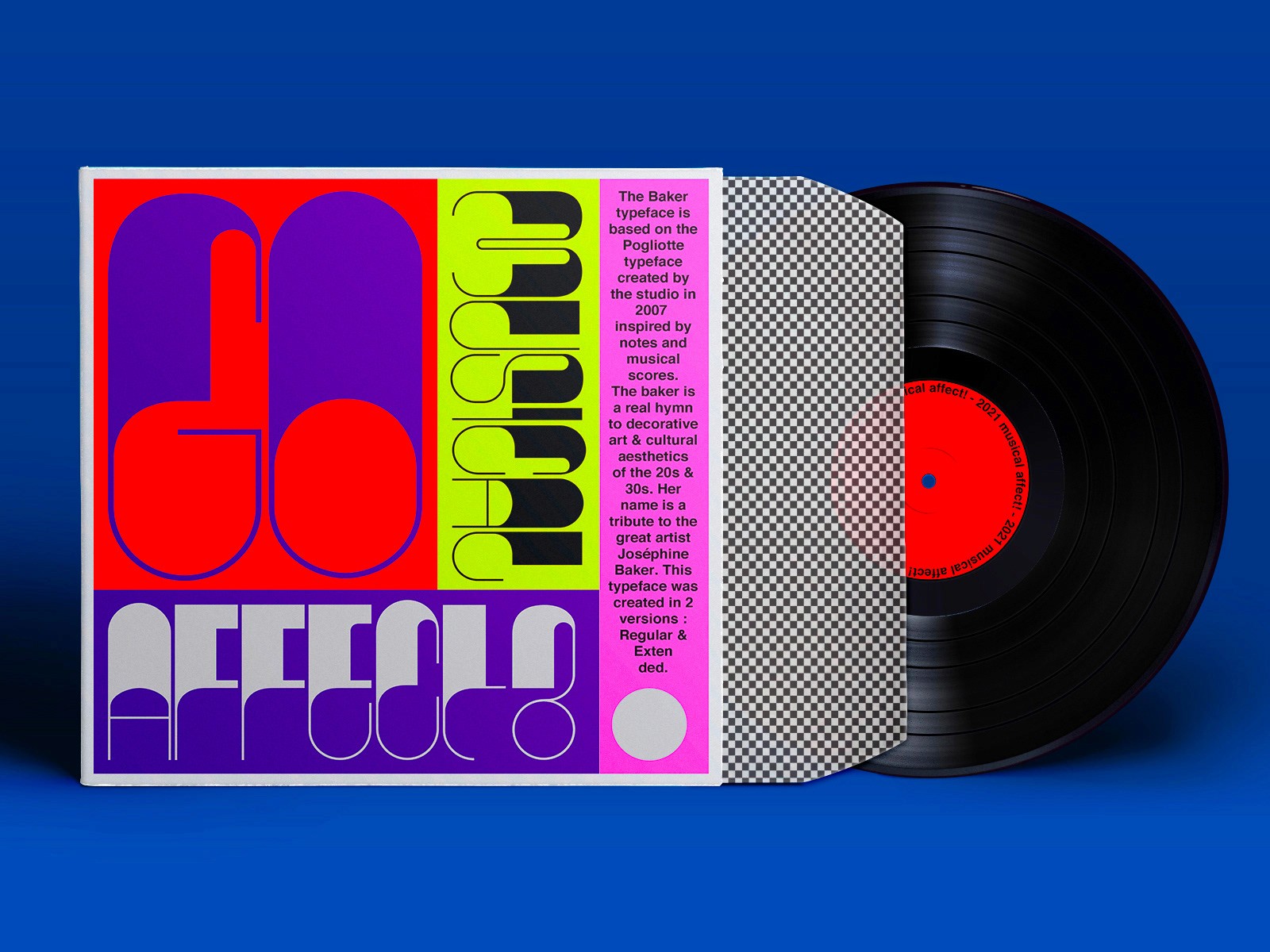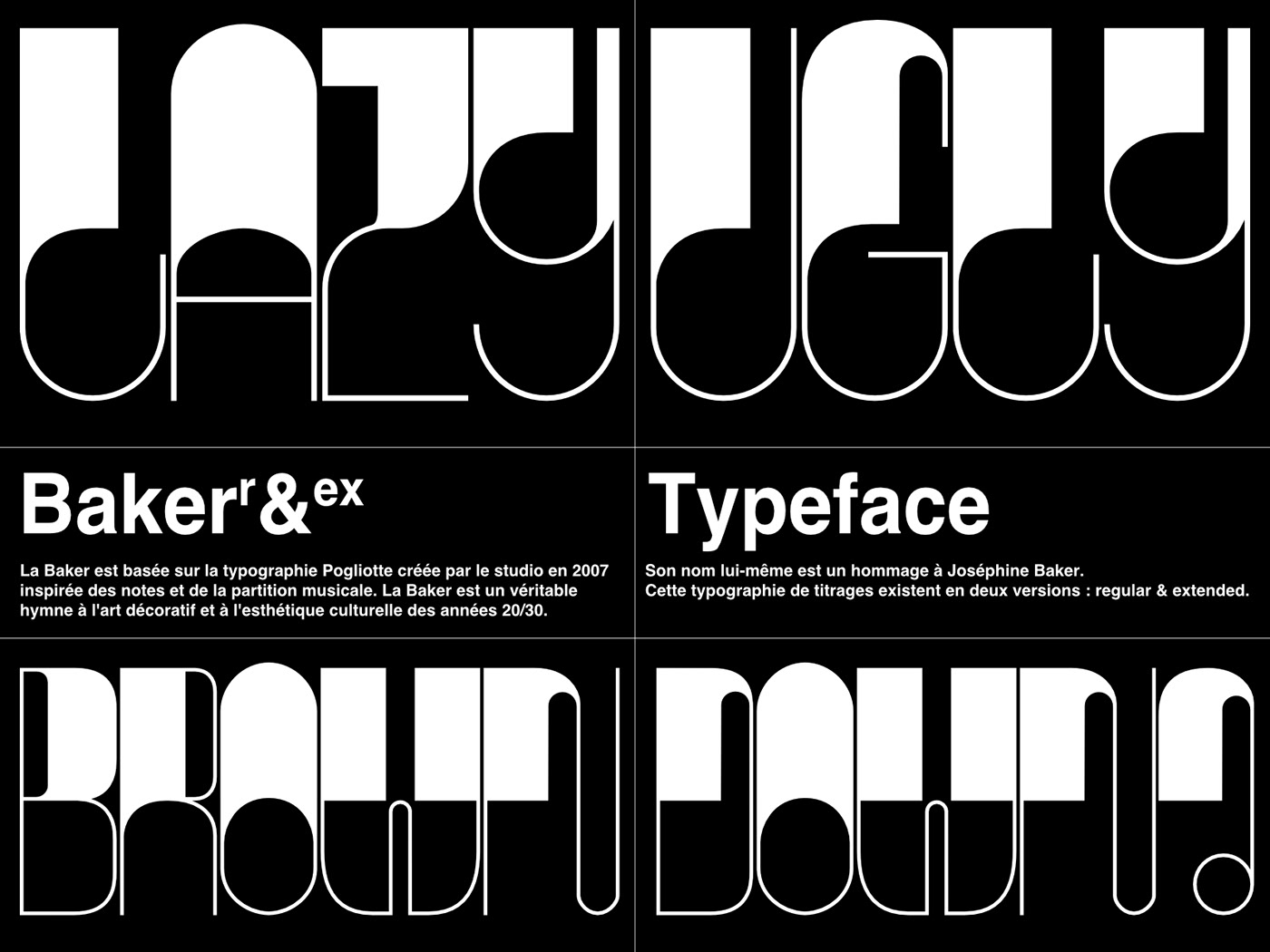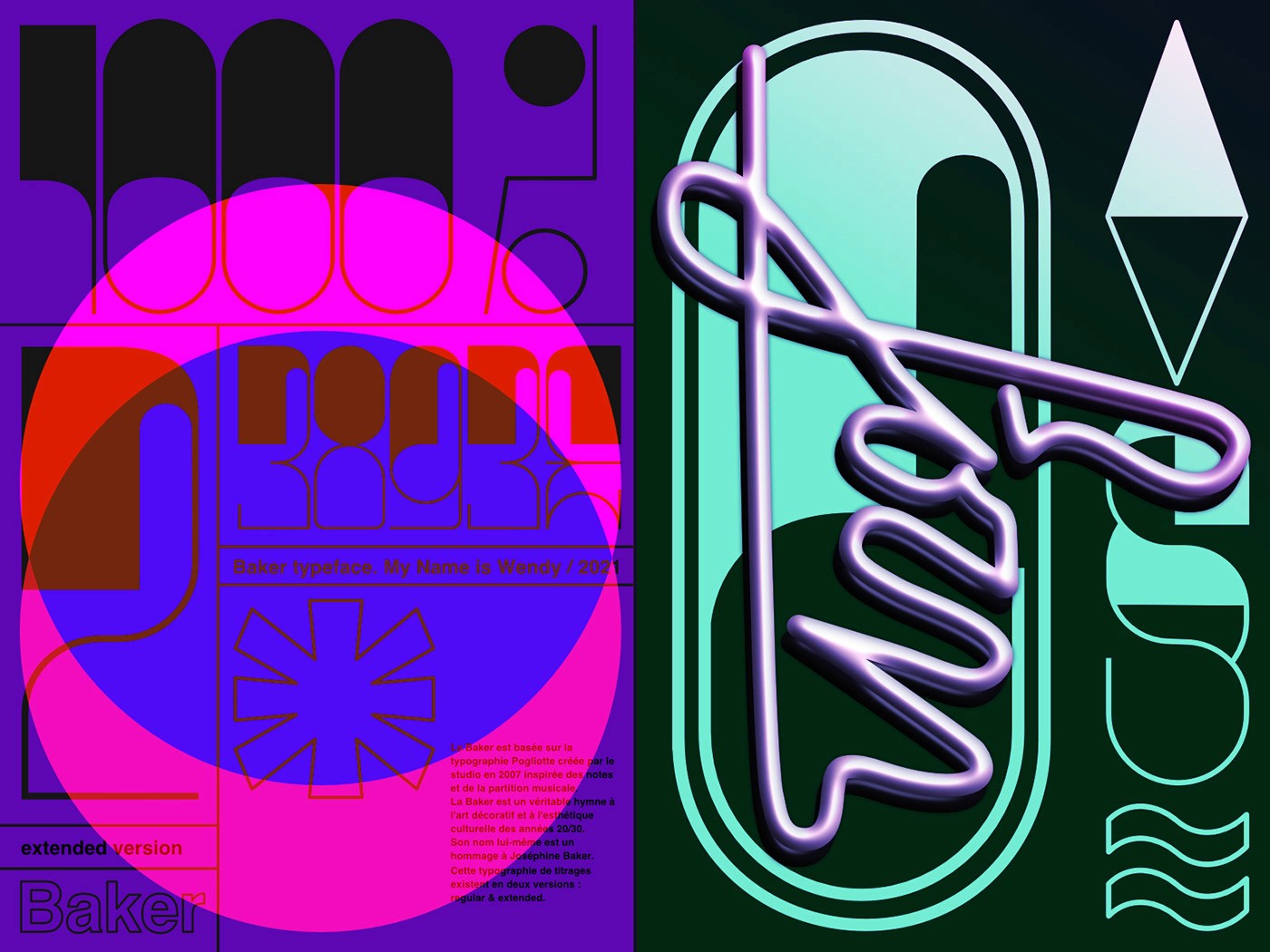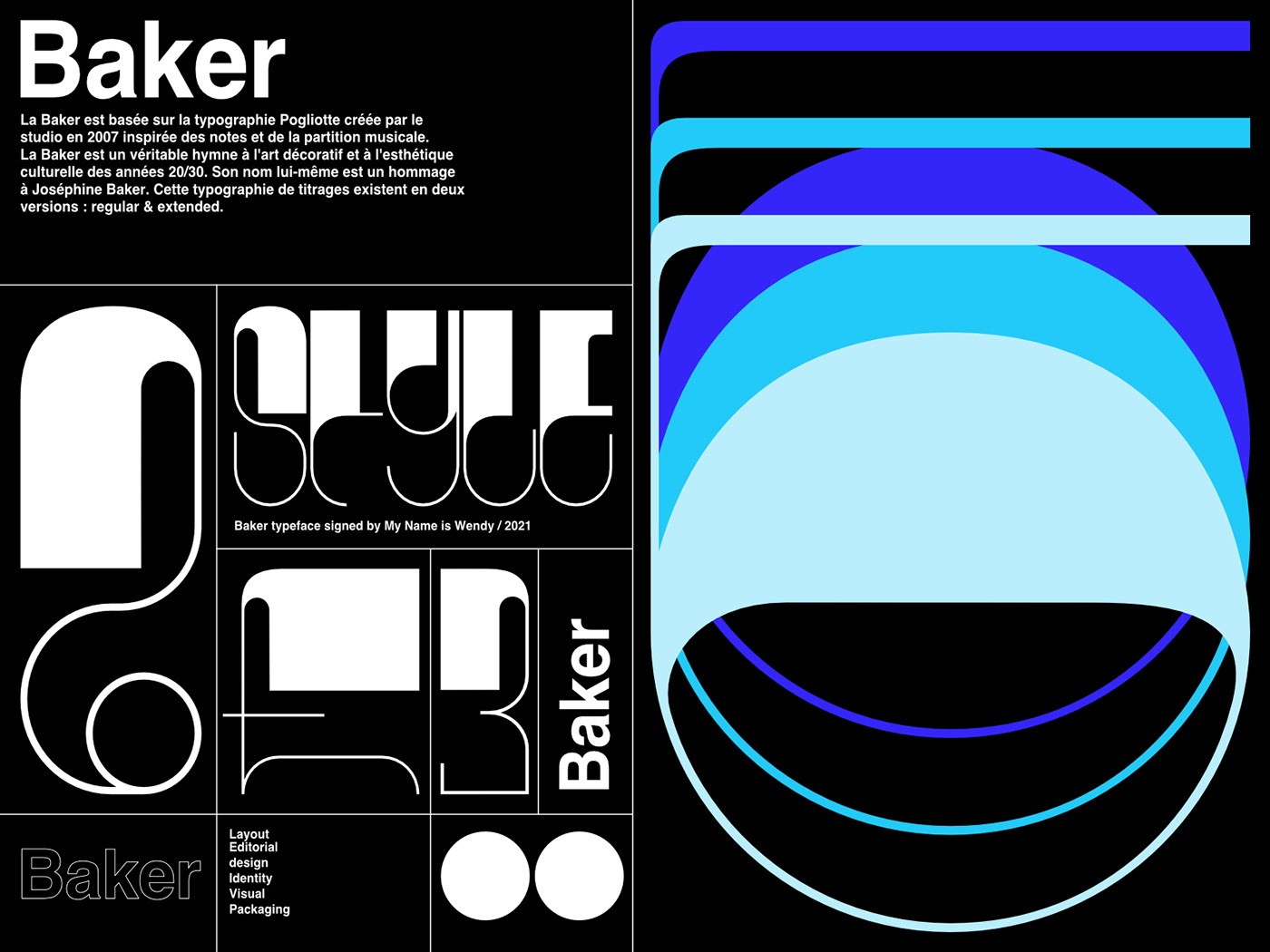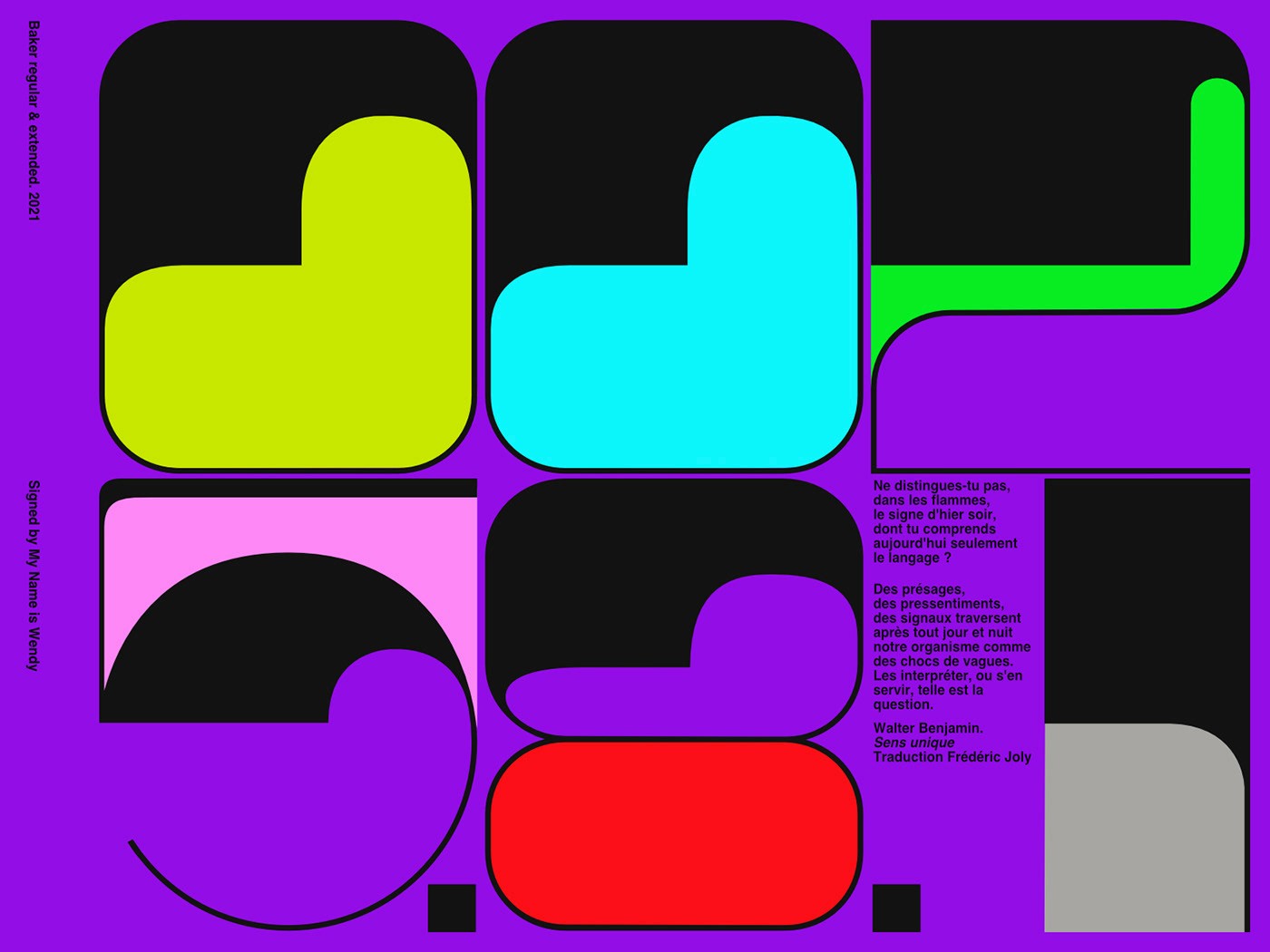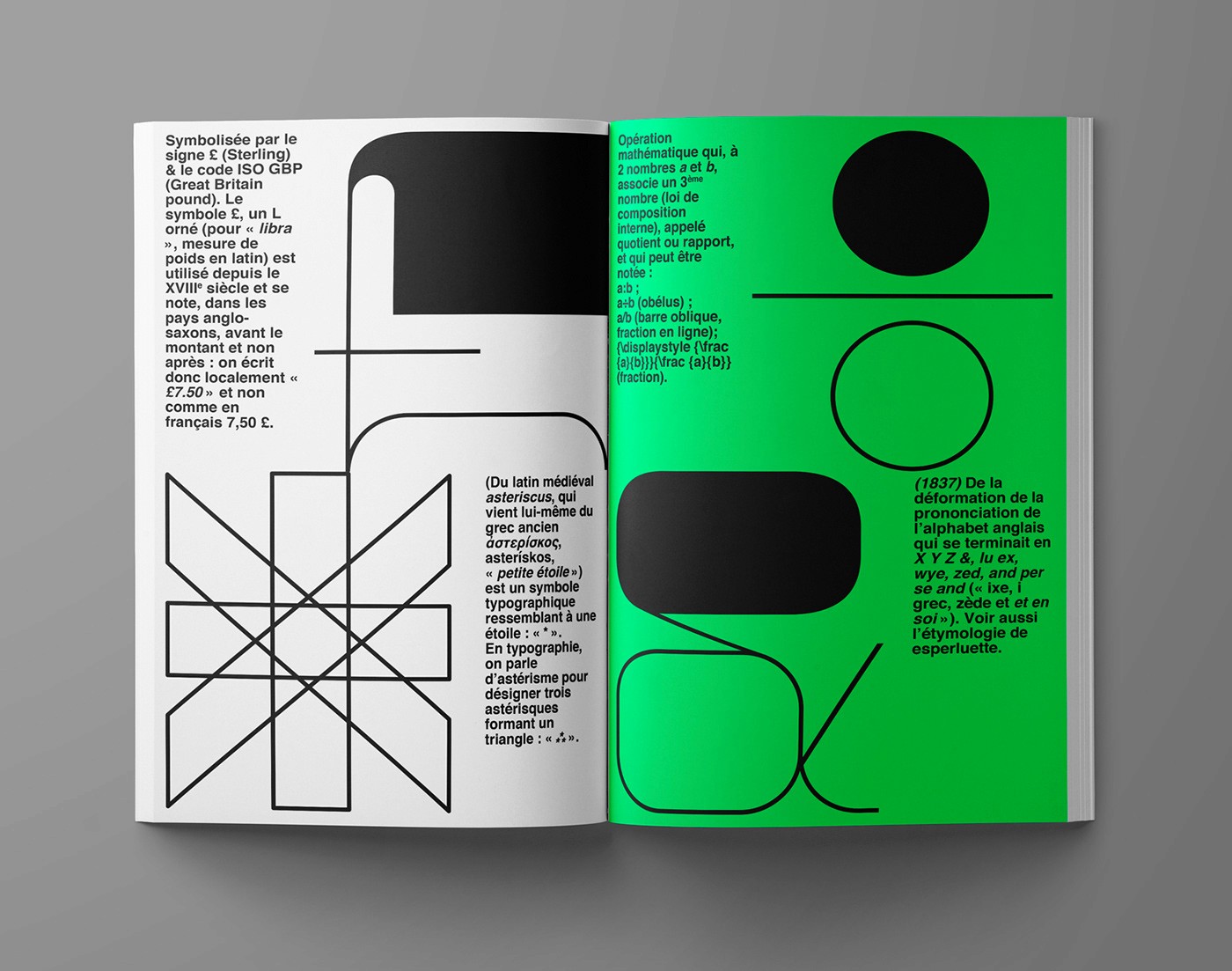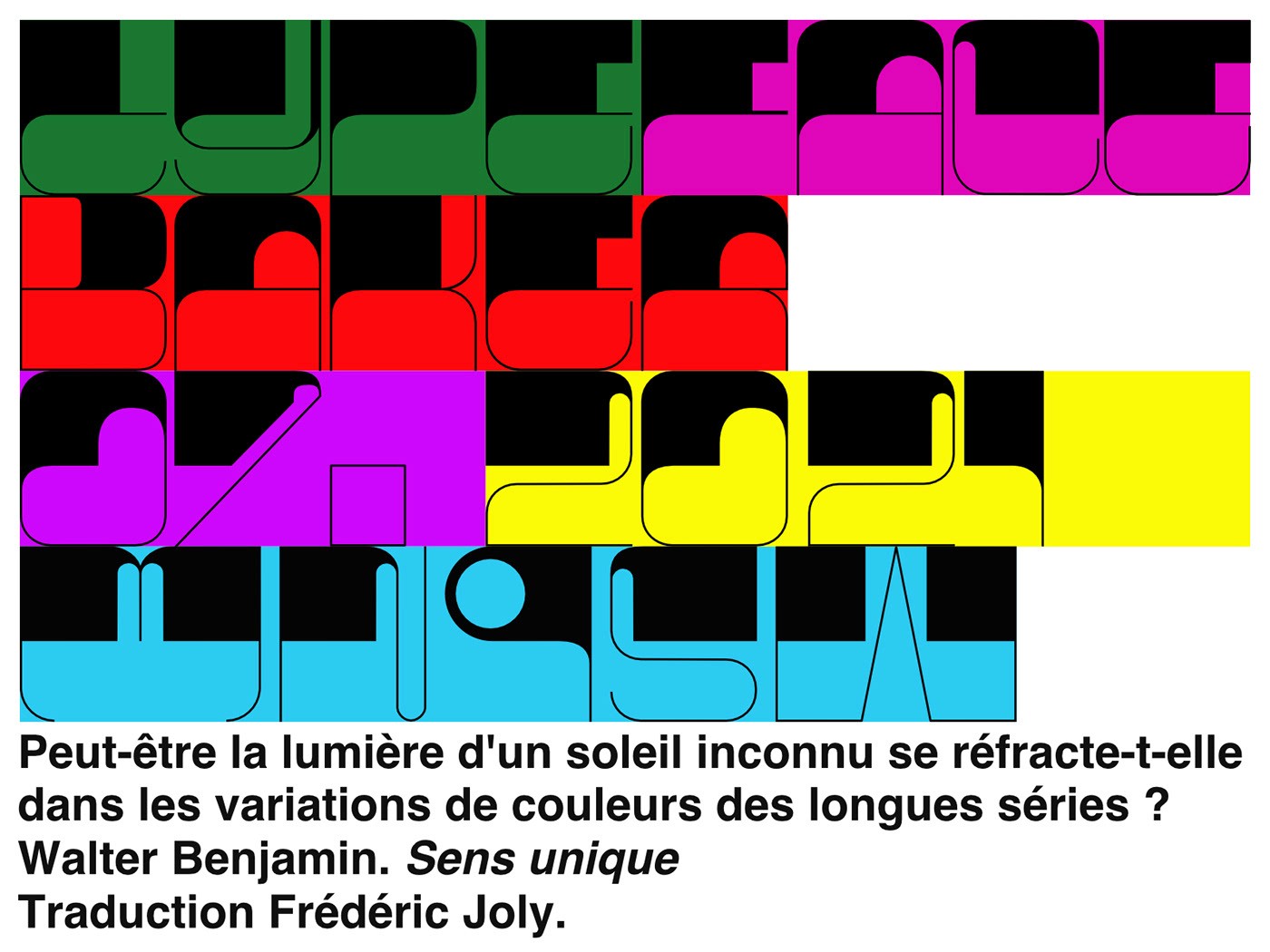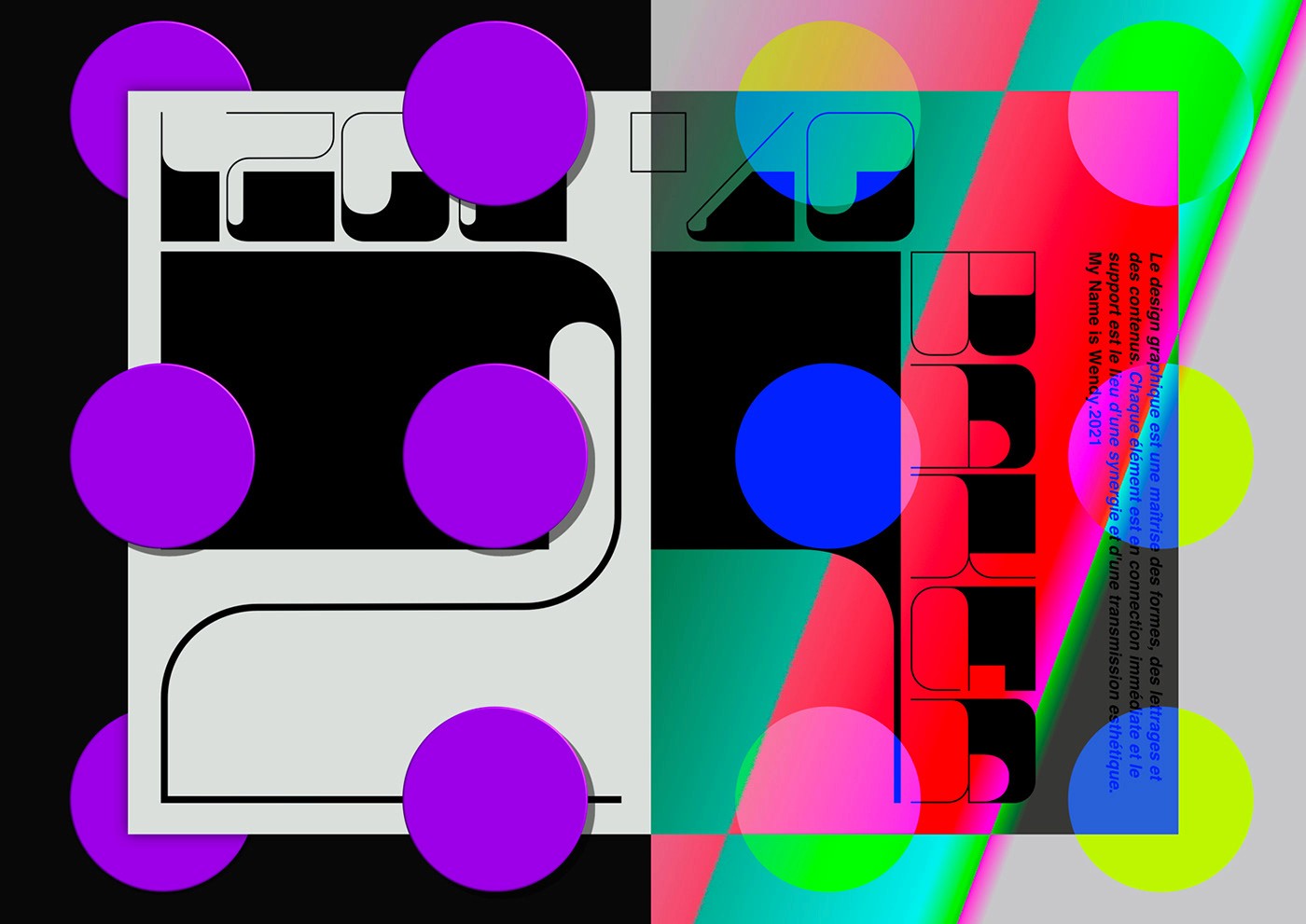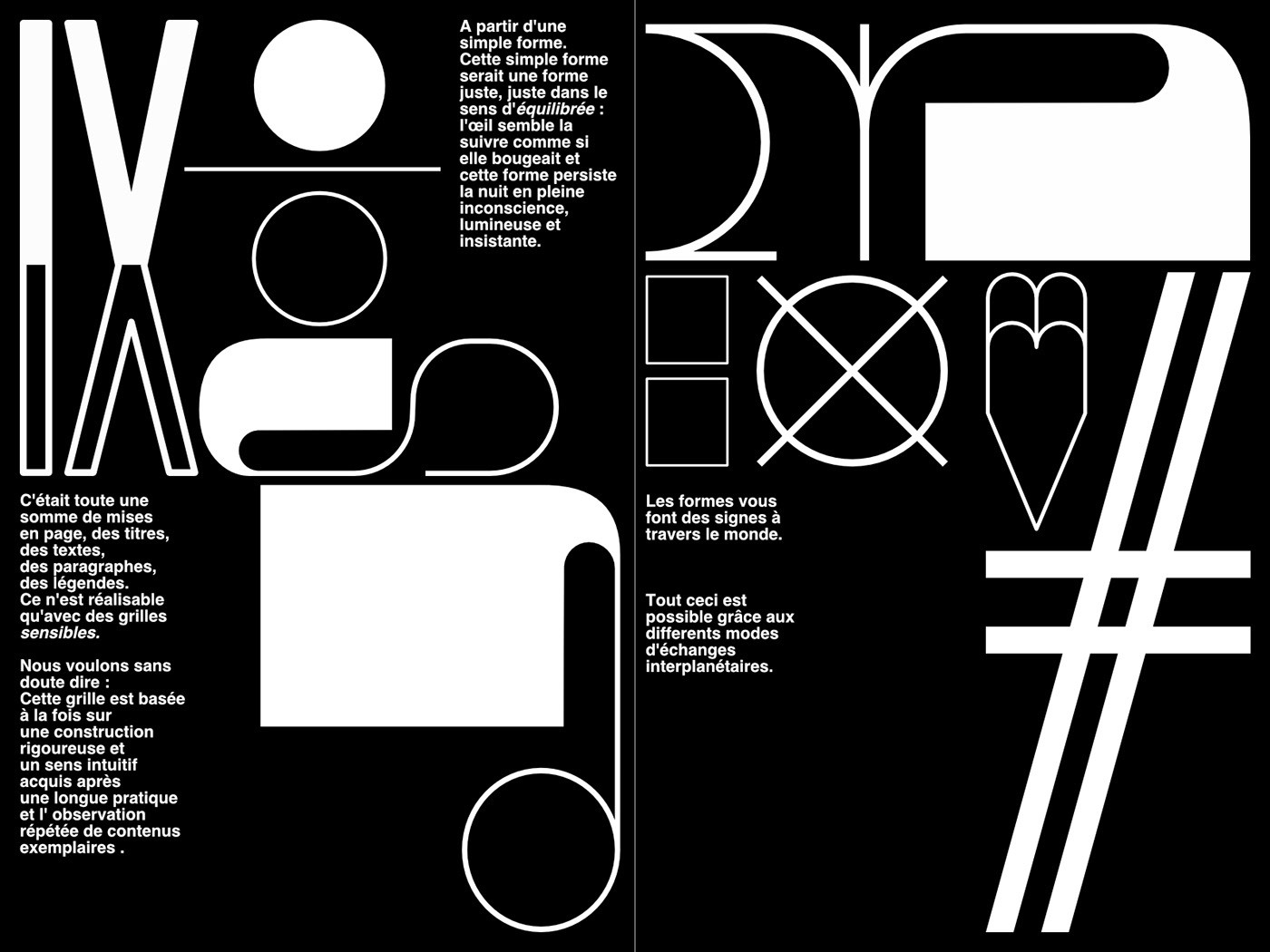
Baker Typeface - Bộ chữ độc đáo từ biểu tượng Josaphine bất hủ
Được truyền cảm hứng từ phong cách đặc trưng của nữ hoàng kịch nghệ tài năng âm nhạc người Pháp Josephine Baker, bộ font chữ Baker Typeface đã đem đến toàn vẹn tinh thần tươi mới và hơi thở phóng khoáng của một trong những biểu tượng có sức ảnh hưởng to lớn nhất trong văn hóa đại chúngMùa hè năm 1926 trong một buổi biểu diễn nhạc Jazz thường niên tại nhà hát nổi tiếng La Revue Nègre (Paris), một nữ nghệ sĩ da màu trong bộ váy độc nhất vô nhị được làm từ 16 quả chuối cao su cùng với những màn lắc hông điêu luyện của vũ điệu Dance Sauvage đầy khiêu gợi và đam mê đã khiến cả đám đông reo hò và gần như điên dại. Và từ đó Josephine Baker đã tạo một tiếng vang lớn và trở thành một hiện tượng văn hóa quyến rũ, xinh đẹp và tài năng.
‍Khi mới thoáng nhìn, ta có thể cảm nhận ngay nguồn năng lượng gần như là bùng nổ của nữ nghệ sĩ đình đám Josephine bởi sự tương phản cực mạnh giữa thân chữ rất dày và chân thì quá mảnh. Tuy nhiên không vì vậy mà trông chúng thô kệch hay nặng nề mà ngược lại đầy tính giai điệu và vô cùng duyên dáng bởi phần chân chữ được tạo hình với những nét cong mô phỏng các nốt nhạc. Và cũng không quá lời nếu ta liên tưởng đến những chuyển động tay chân nhuần nhuyễn điêu luyện của cô. Hơn thế nữa, phần dày nhất của bộ font chữ cũng rất tinh tế gợi đến hình ảnh nụ cười với hàm răng trắng sứ tỏa sáng đặc trưng đúng chất Josephine. Chính vì tính liên tưởng siêu bay bổng đến từ font chữ này mà nó có thể được sử dụng theo phong cách retro vô cùng phù hợp, còn thể hiện cho các ấn phẩm mang nét hiện đại thì lại toát ra vẻ đẹp vô cùng phá cách.
‍Chỉ cần sử dụng với kích cỡ lớn và nền màu trơn là ta đã có thể phô hết những nét đẹp vốn có của Baker Typeface. Chưa dừng lại ở đó, sự tương phản giữa màu nền và màu chữ cần phải thật cao để không bị mất nét. Ứng dụng Baker Typeface sẽ không hoàn toàn quá khó khi bạn biết kết hợp nó với bảng màu tươi nổi bật và phong cách thiết kế art decor.